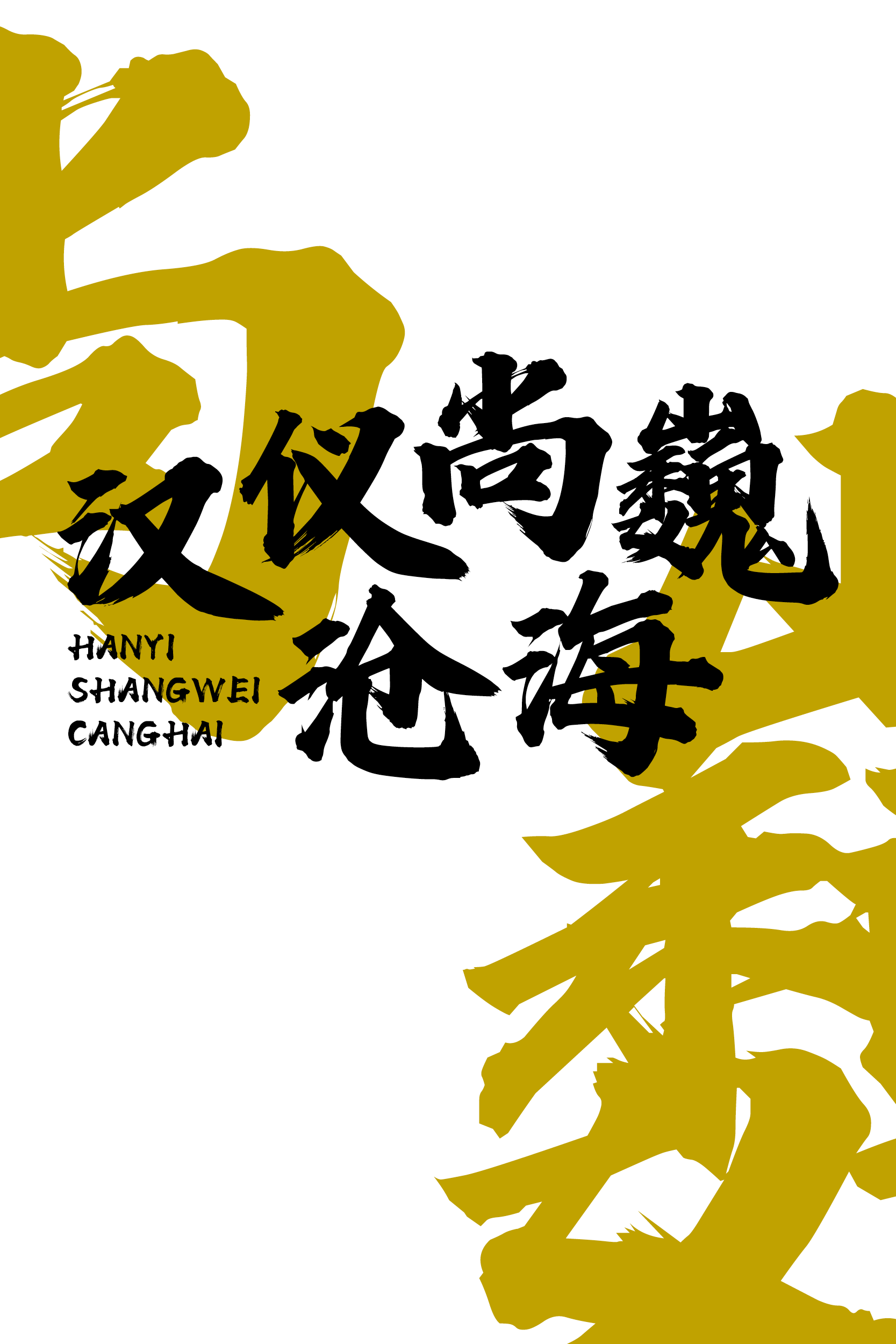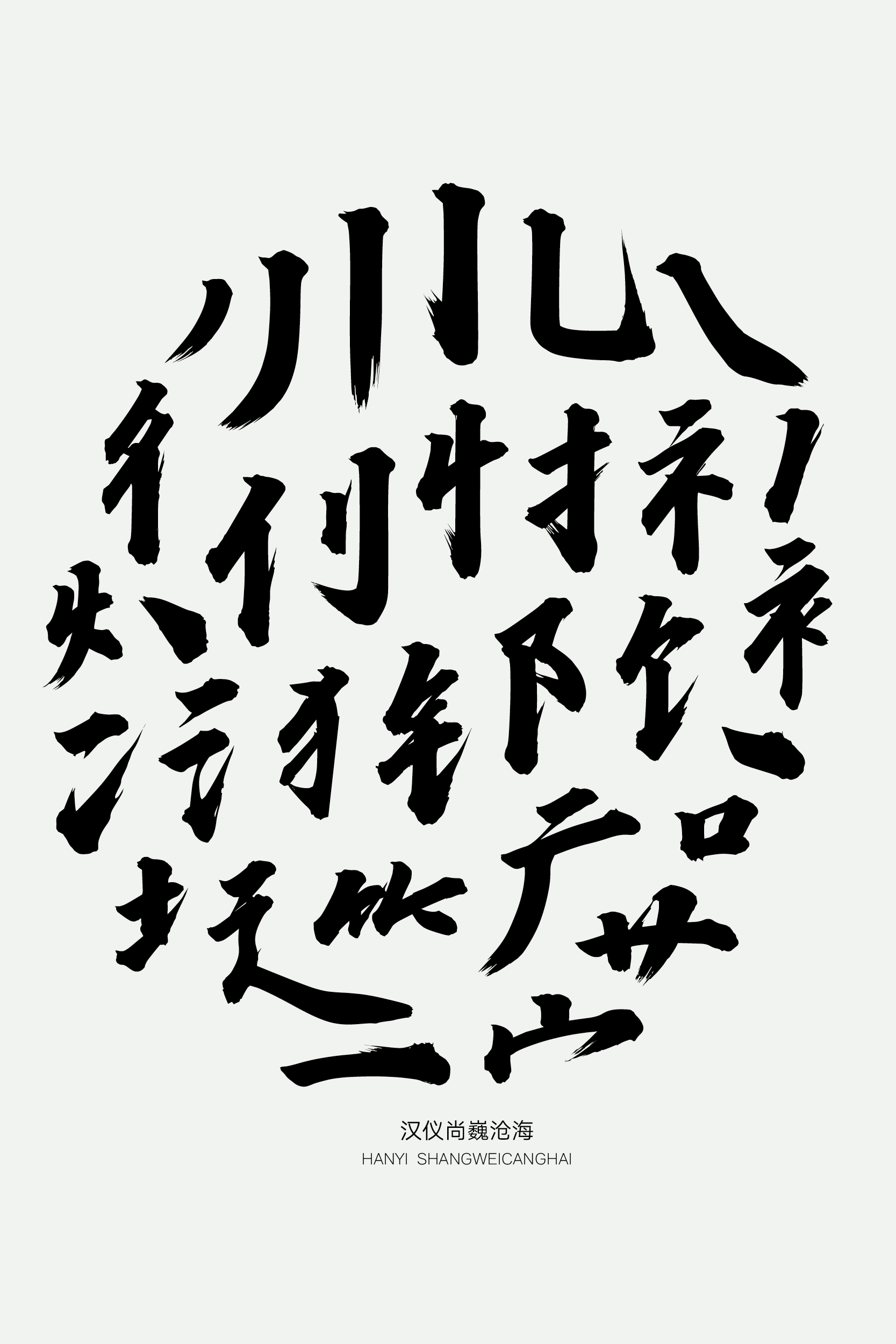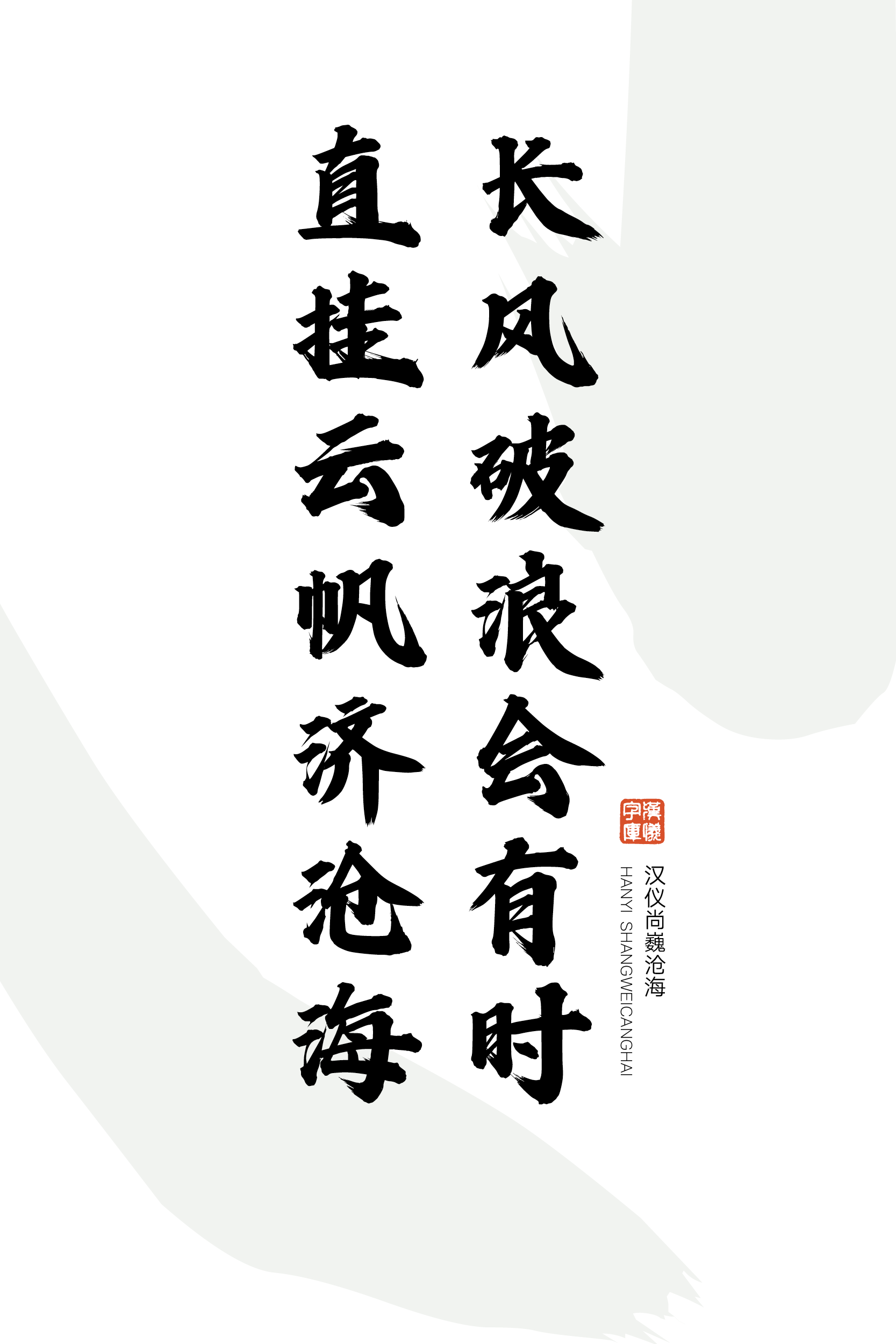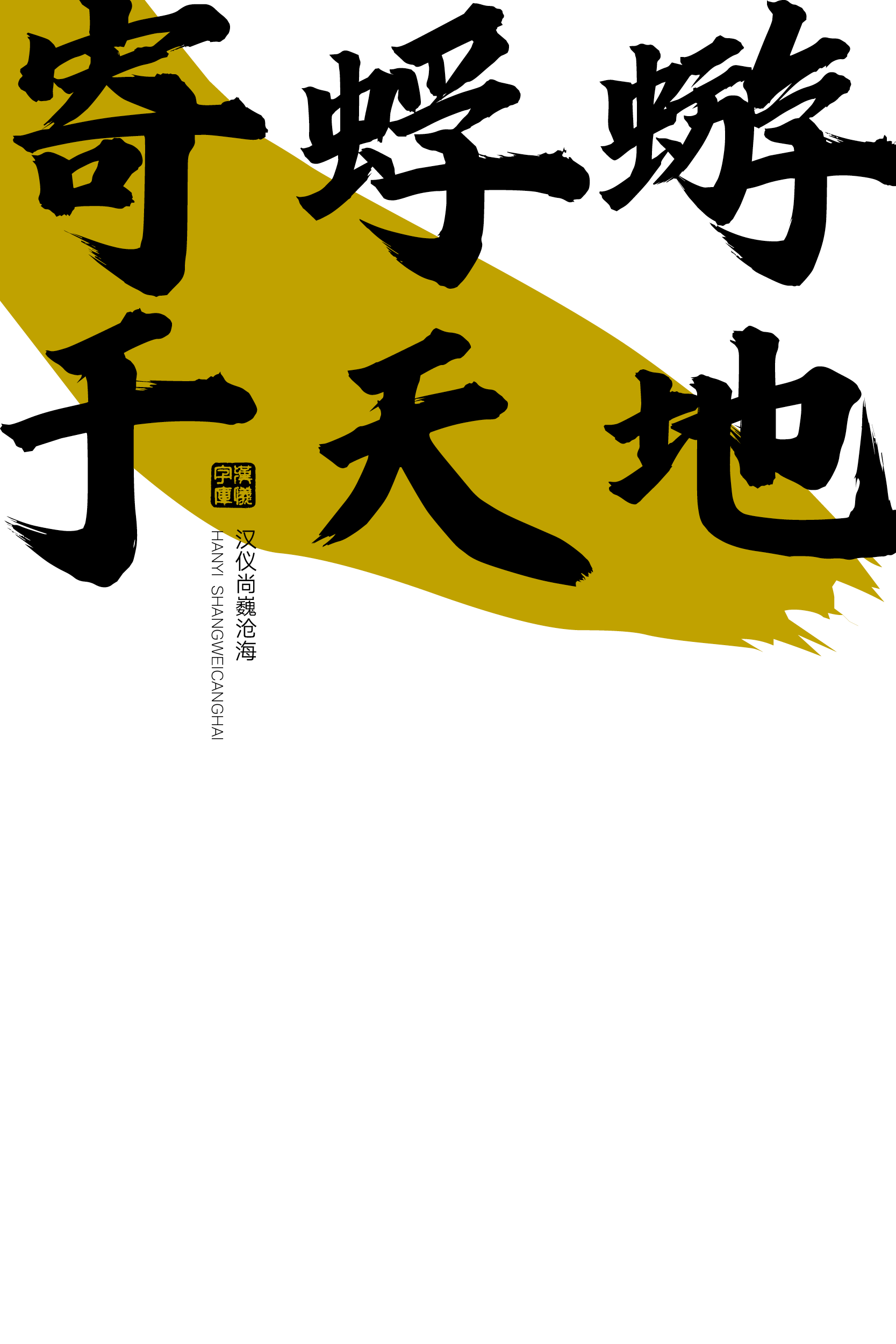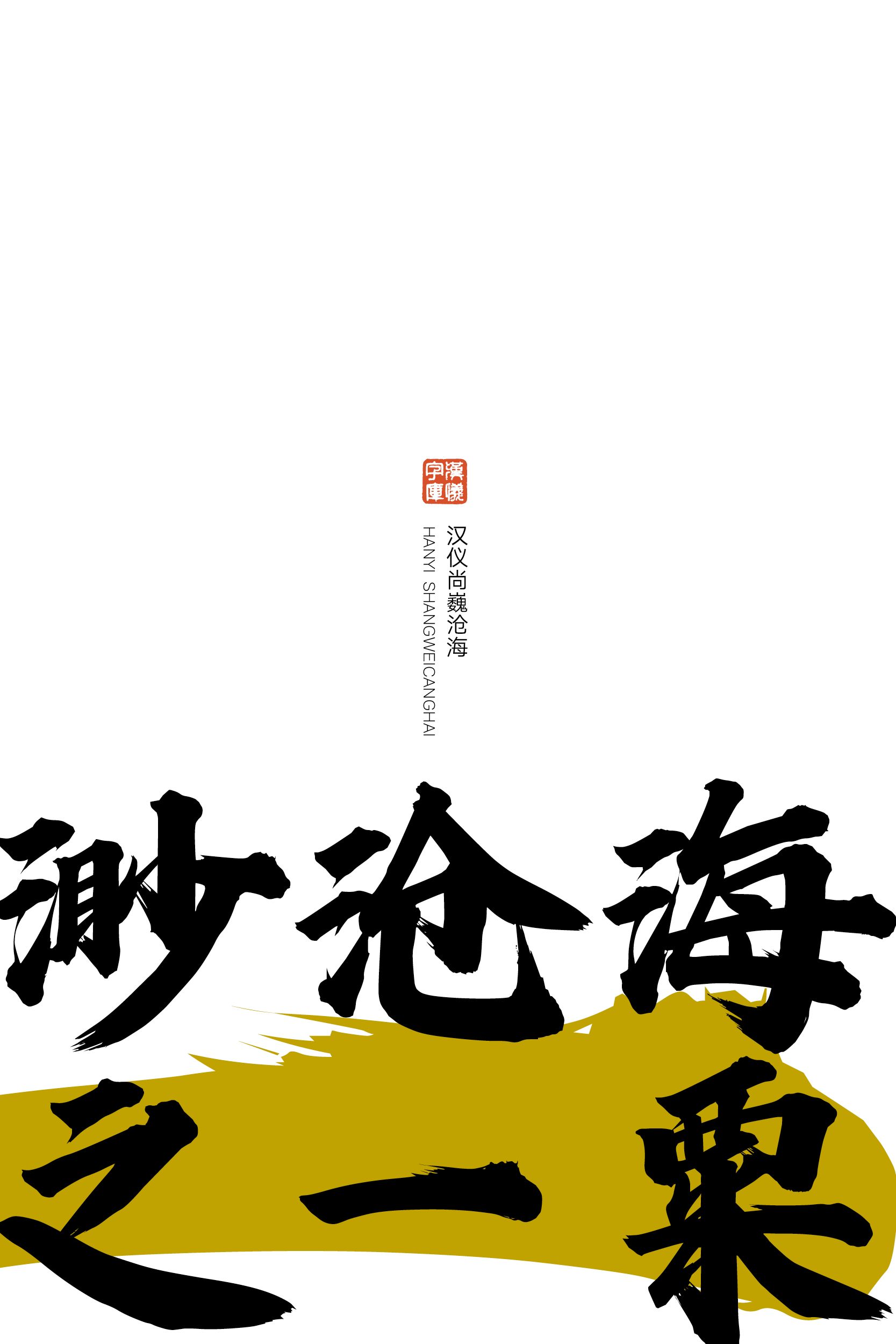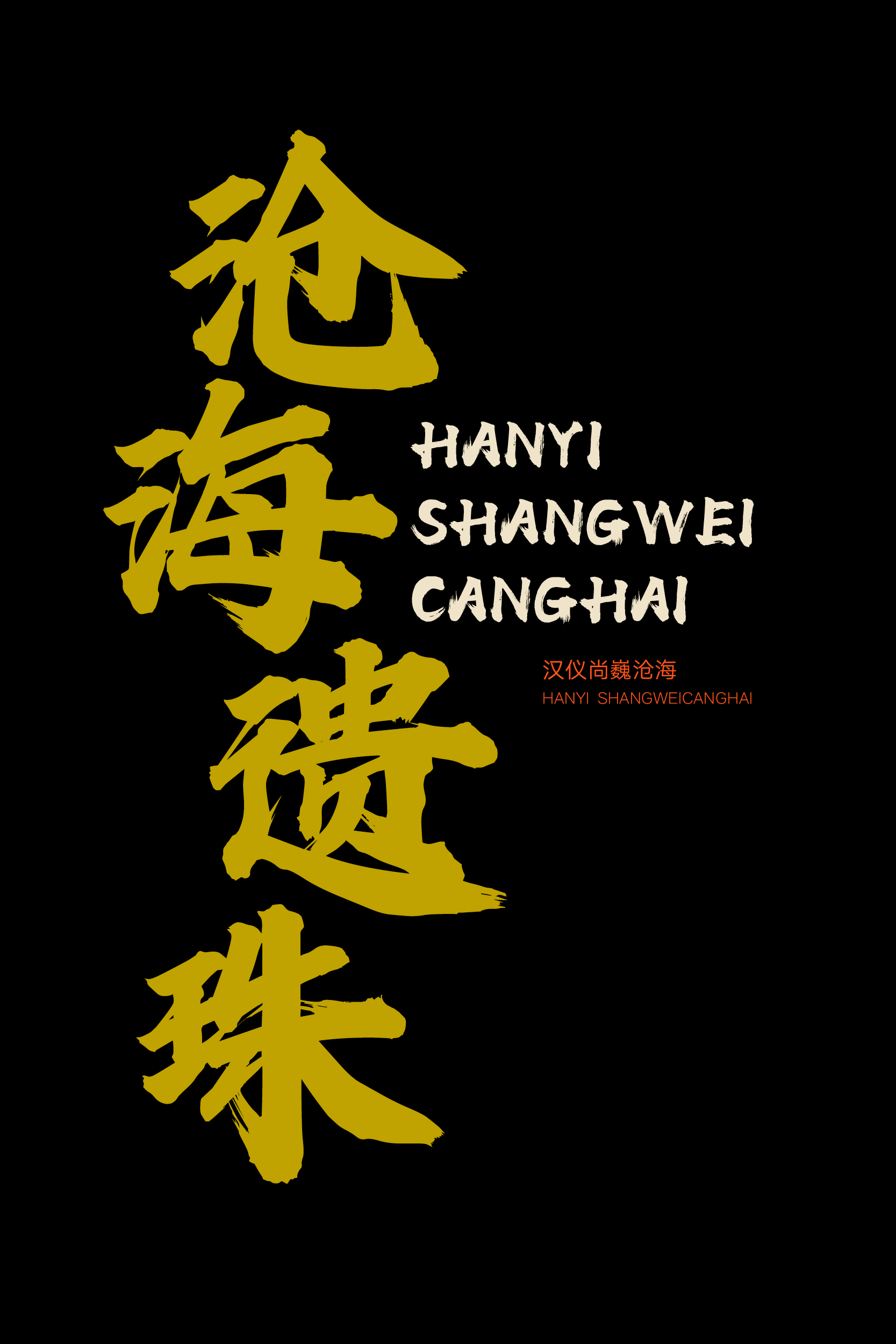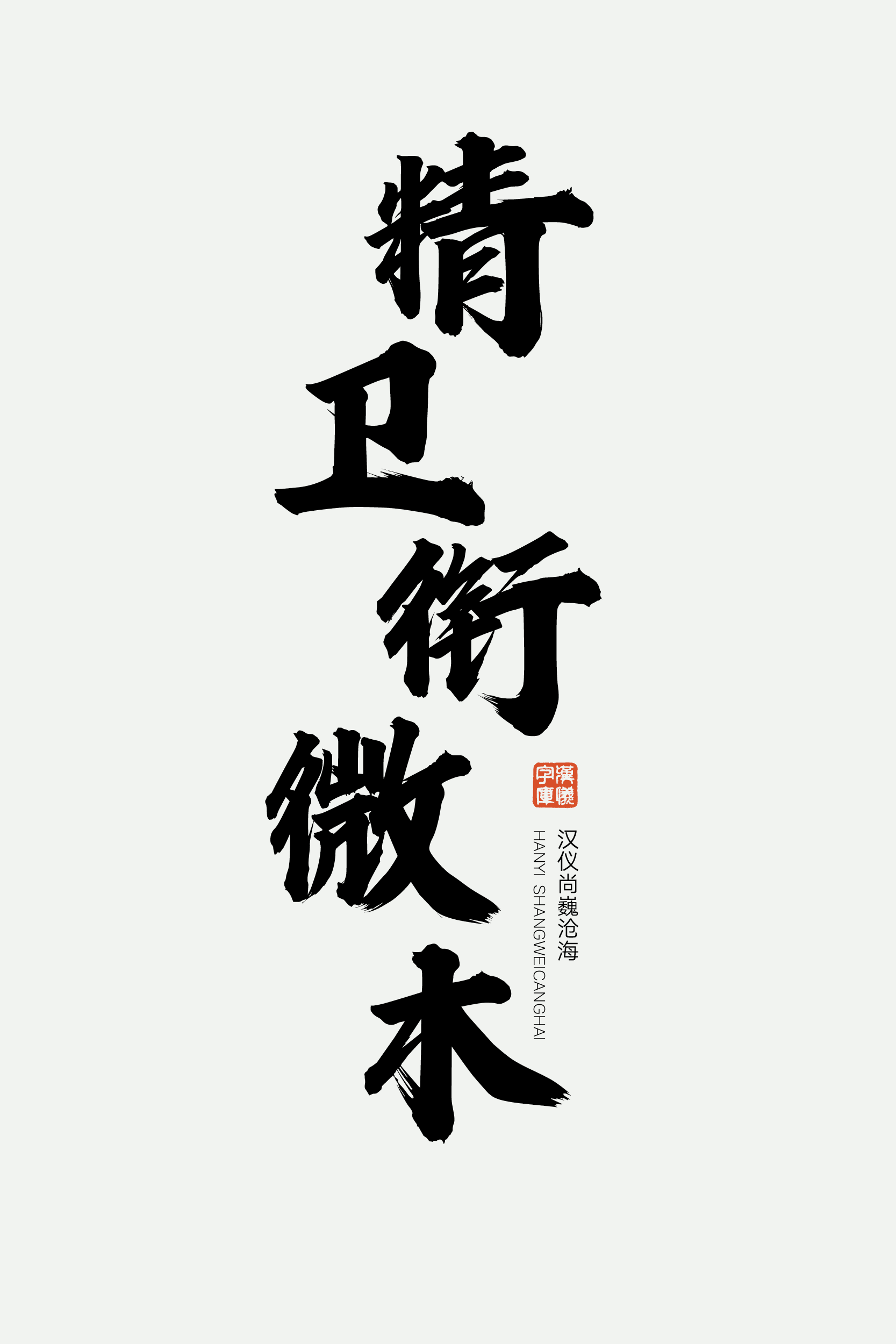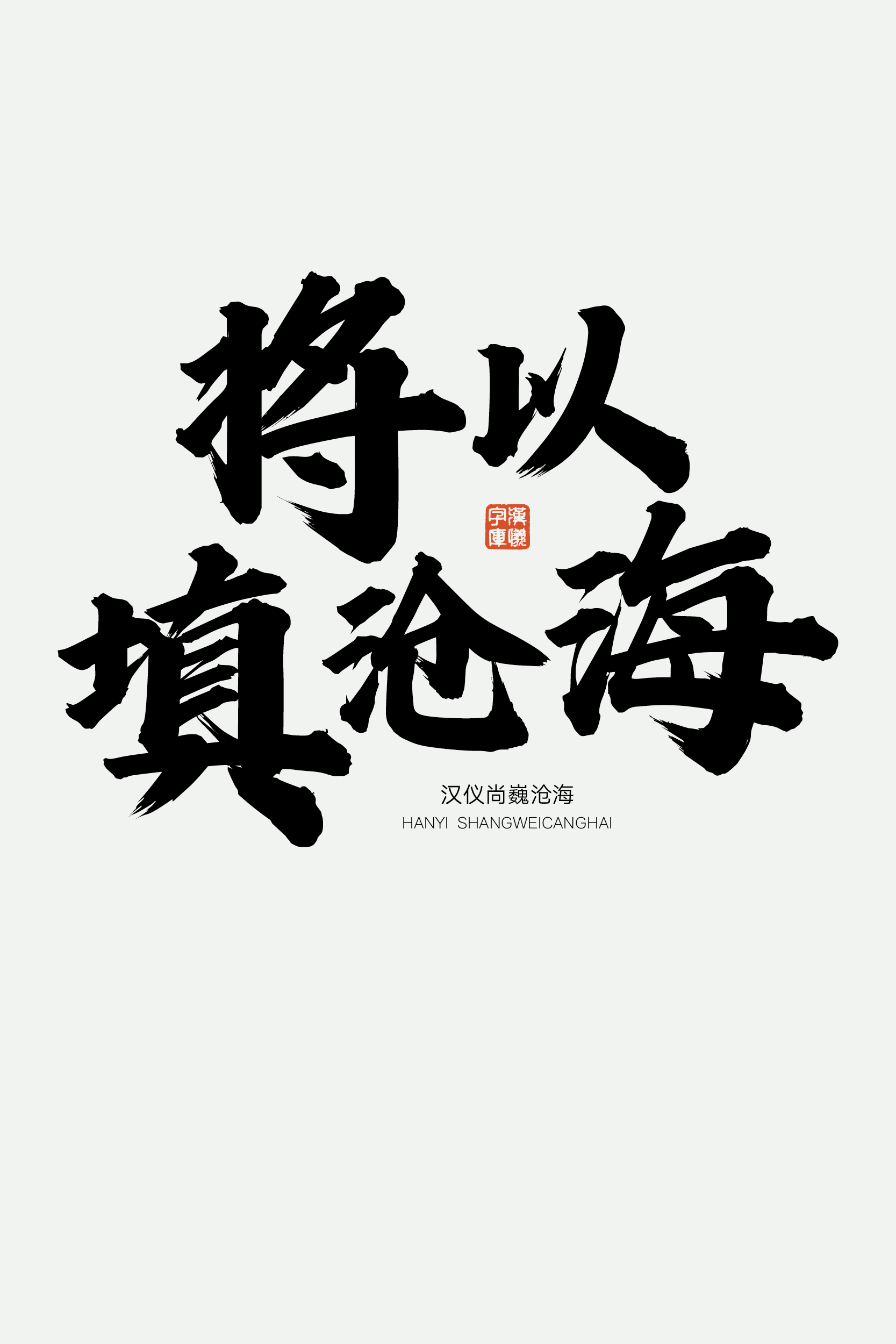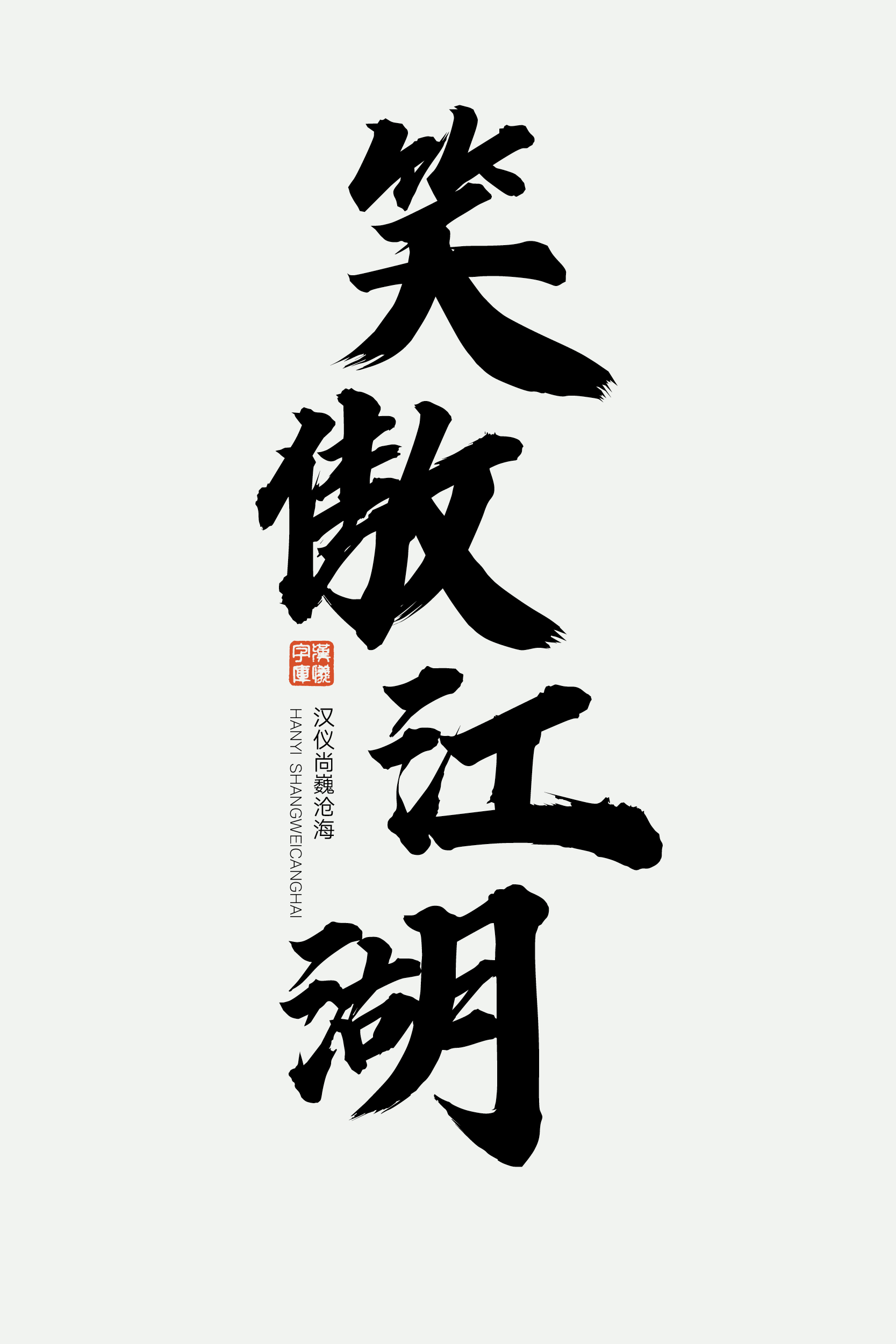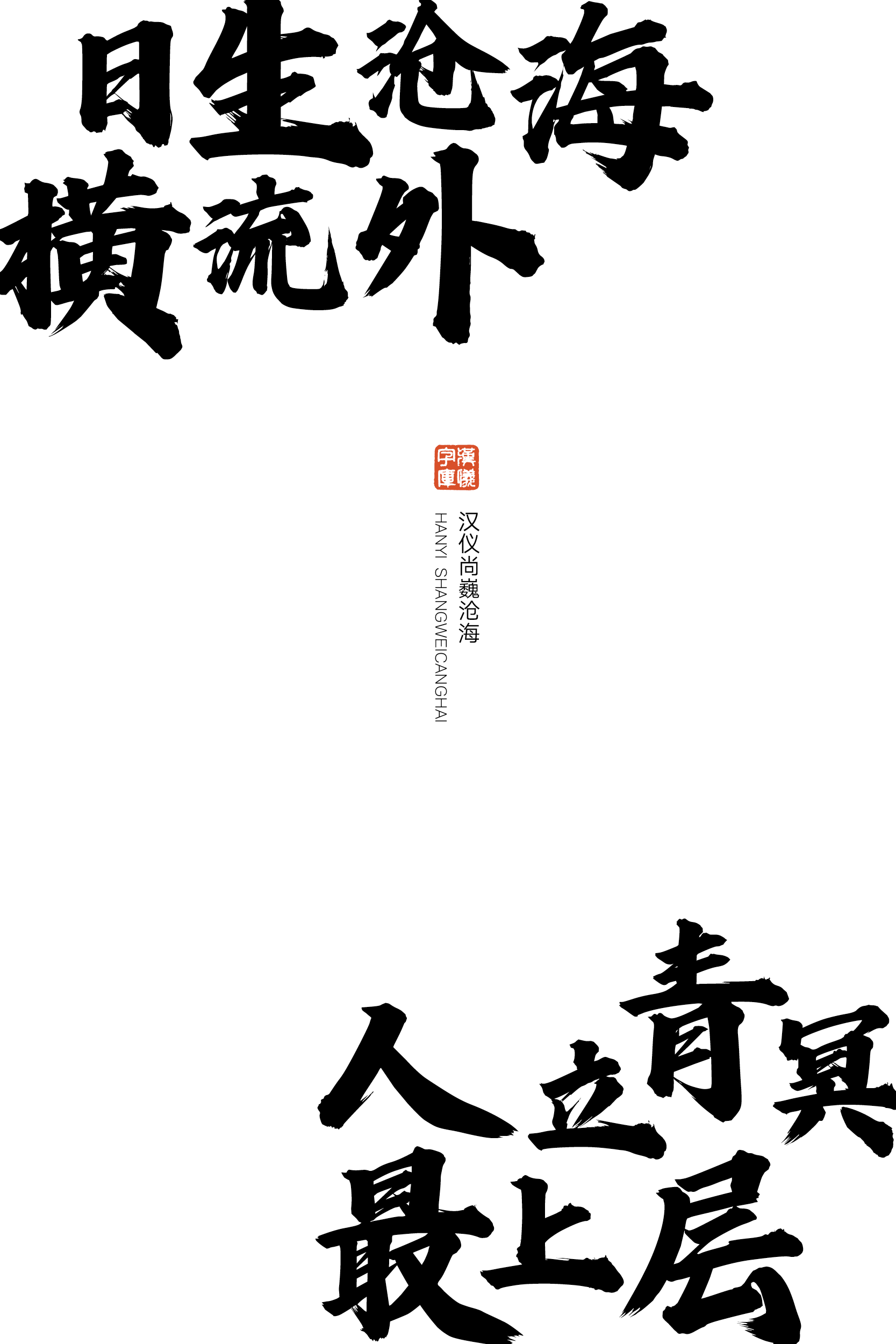
汉仪尚巍沧海
书写字体
书写 / 豪放 / 力量
汉仪尚巍沧海是一款具备浩然之气的手写标题字,豪放有力,表现力极强。该字体以结构的左收右放和笔画大小的比例、分布营造出有透视角度的空间感,搭配夸张的收笔和捺画使排版标题时显得更有张力。整体排版整齐稳定,大小错落排版使手写效果更加丰富,适用于影视娱乐、休闲餐饮等各种场景。
字形结构上,这款字体的中宫收紧,重心偏高,左收右放。
笔画浑厚、粗壮、醒目,豪放而有力量。
笔势连贯流畅,富有书写味道的牵丝、飞白为这款字体增添更多的细节。
汉仪尚巍沧海的西文部分字形工整端正,x高(x-height)较小,转而强调升部高度(ascender height)和降部高度(descender height),以匹配中文部分收紧的中宫和偏高的重心。笔画同样具有书写张力,遒劲豪放。